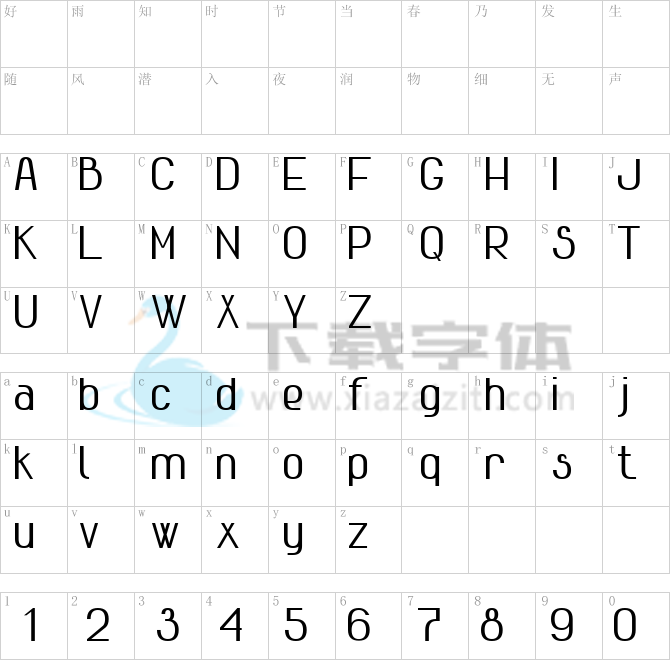
Advanced Sans Serif 7.ttf字体下载,这款字体结构工整、笔画清晰,兼顾美观与易读性,适用于标题、正文、海报、包装、LOGO 等多种场景。字形优雅稳定,风格百搭耐看,适配日常排版与创意设计,让文字呈现更舒适、更具质感。Advanced Sans Serif 7.ttf字体下载一笔一画,皆是细节,以均衡的比例、流畅的线条打造舒适视觉体验,字形端正大气,风格简约现代。无论是商业设计、品牌宣传还是日常排版,都能轻松驾驭,让文字更有格调与力量。Advanced Sans Serif 7.ttf字体下载字体下载。